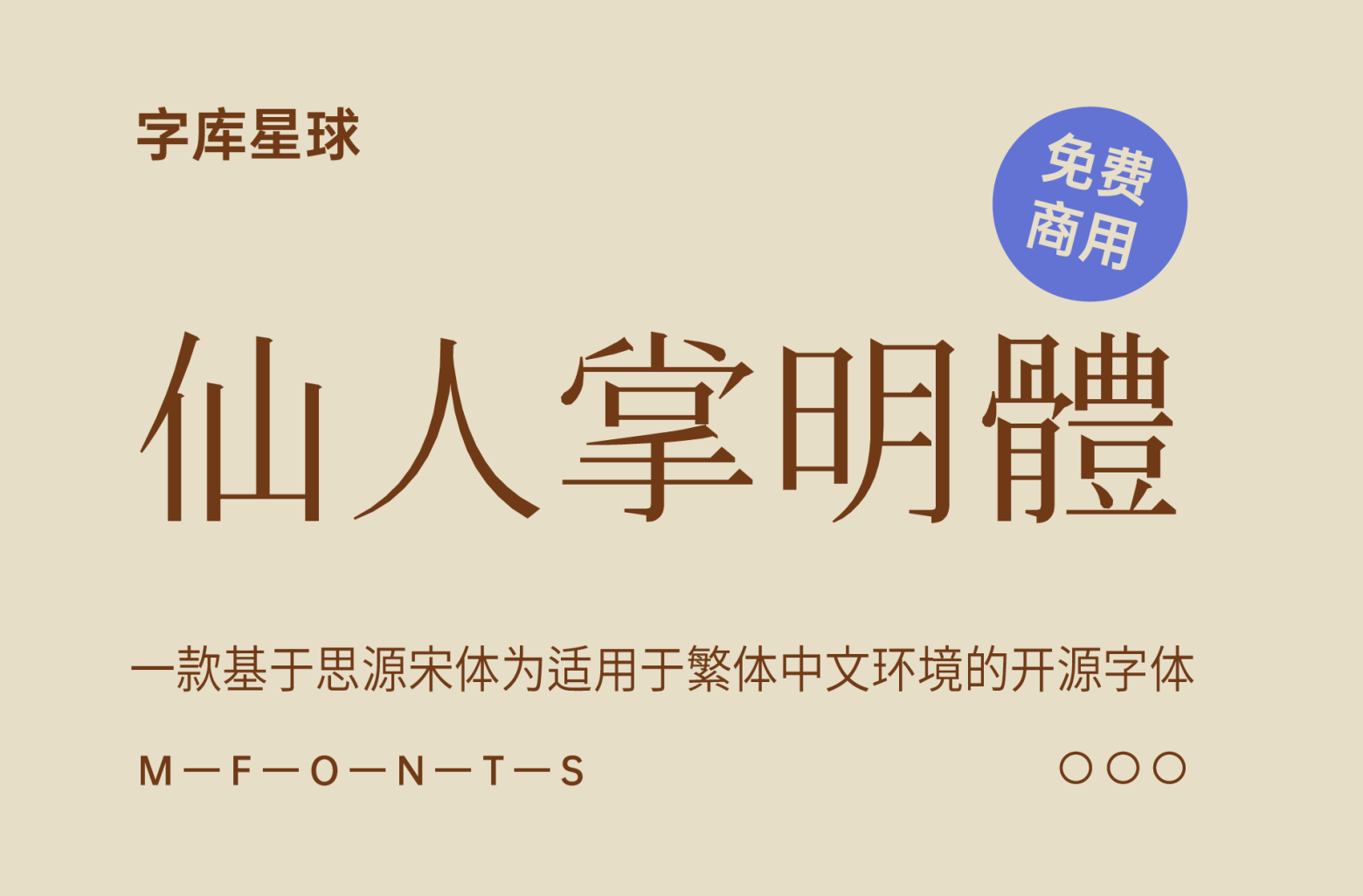
仙人掌明体
仙人掌明体(Cactus Classical Serif)为适用于繁体中文环境的开源字体,主要制作者为田海东,宇文满月参与制作及维护。
仙人掌明体以Henry Chan开发的「香港民间字集传承字形版」字体及其于字形维基(Glyphwiki)登录的字图为基础,并以But Ko基于「思源字体」开发的「源样明体」字体补充西文及其他字符,局部参考传承字形,包括传承字形标准化文件的推荐形体,与其他常见的传承字形,把字形修改为中文传统的形体,并补制一些欠缺的汉字。
另有特殊版本「简繁转换版」,收录字数较少,方便把简体文件显示成繁体中文。但它包含的字符都比较少,请确定有必要才使用它。此版本以GuiWonder开发的「中文字体简繁处理工具」制作。
本字型由Henry Chan绘制主要字图,田海东主力制作,宇文满月参与修改,以应付屏显和排印之需。
本字型借用了Steve Yuu、But Ko的开源贡献而制作。